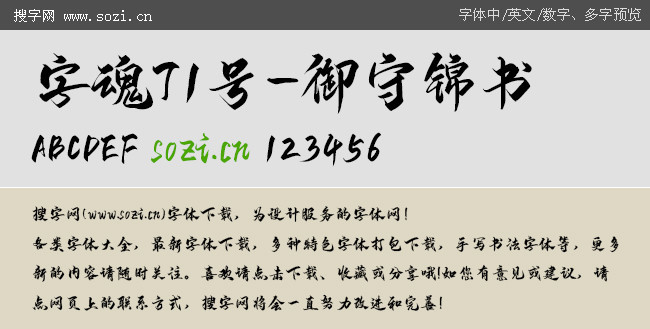
字魂71號-御守錦書
搜字網(wǎng)提供一款字魂71號-御守錦書中文字體下載,該字體是一款毛筆書法手寫字體,該字體包含6763個中文、字母、 符號和數(shù)字,具有溫柔、婉約、手寫風(fēng)、簡約 的風(fēng)格,可以滿足您設(shè)計上的各種需求,該字體主要用于印章、企業(yè)店鋪、廣告、影視傳媒 等場景。